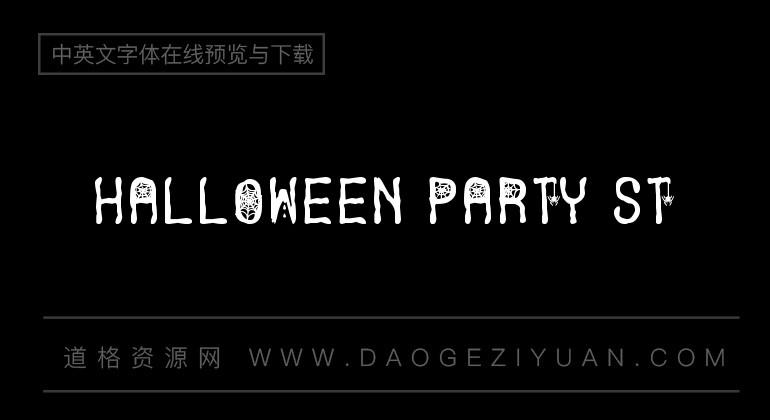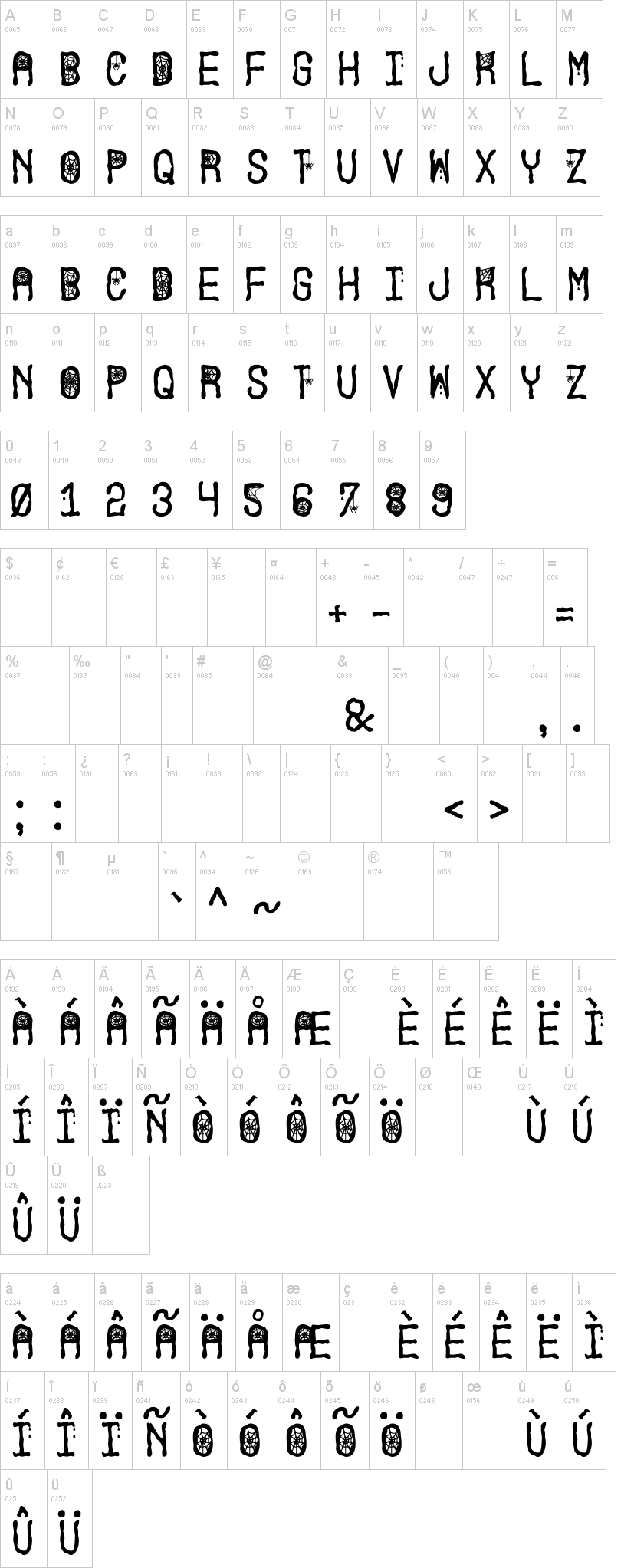
Halloween Party St
Halloween Party St 字体是一款具有节日气息的手写体字体,它具有节日气氛浓厚的特点。字体风格活泼、活跃,极具节日气氛,是用于节日海报、节日信息、节日活动等场合的理想字体。它的特点是字体简洁,笔画清晰,线条流畅,层次分明,可以更好地表达出节日的活力和热情。
Halloween Party St是一款非常不错的手写艺术字体,具有很好的视觉感,适合于文化类的宣传设计、商业类品牌的广告和产品包装设计以及个性化文字排版等较多场景。